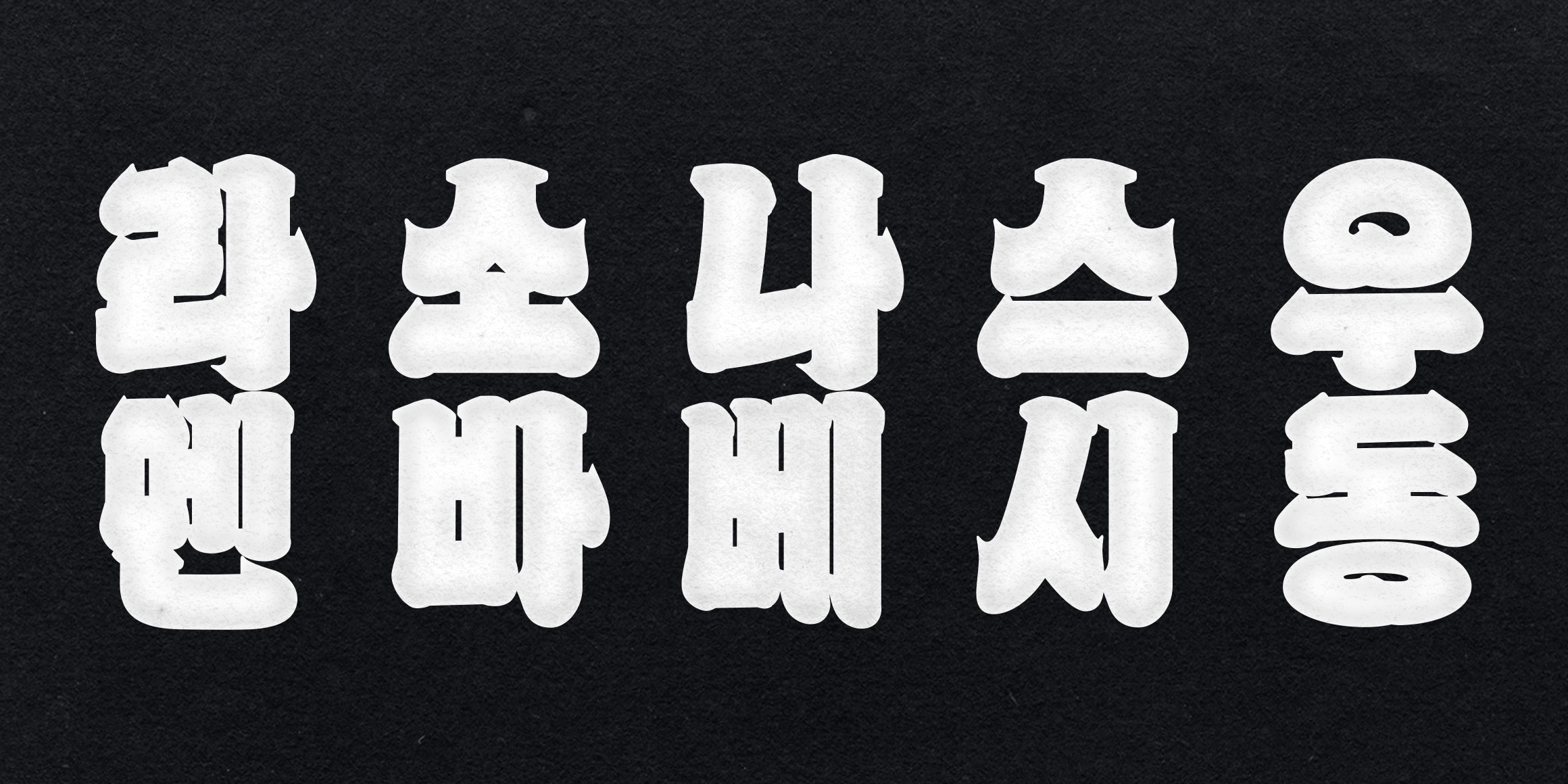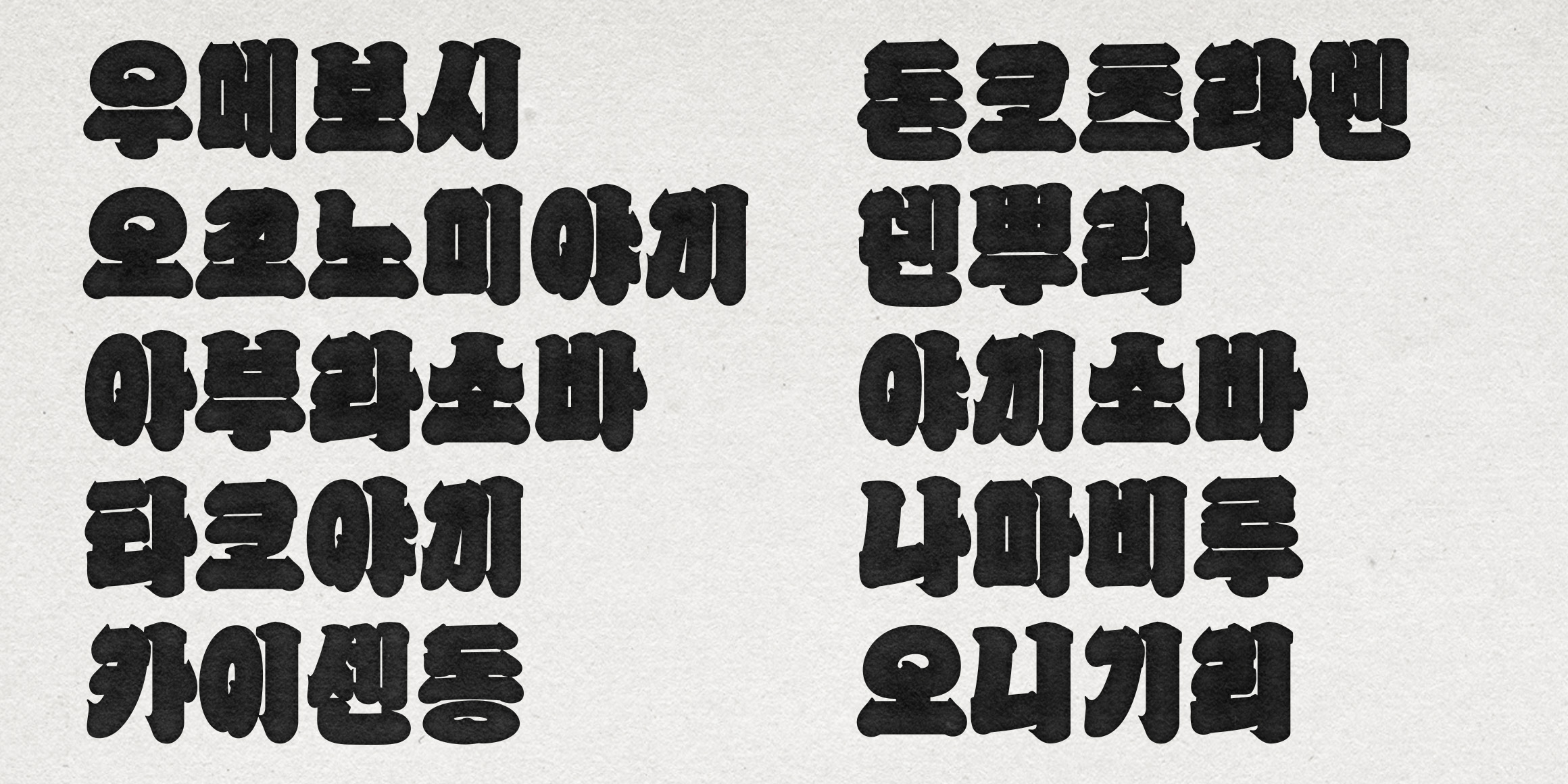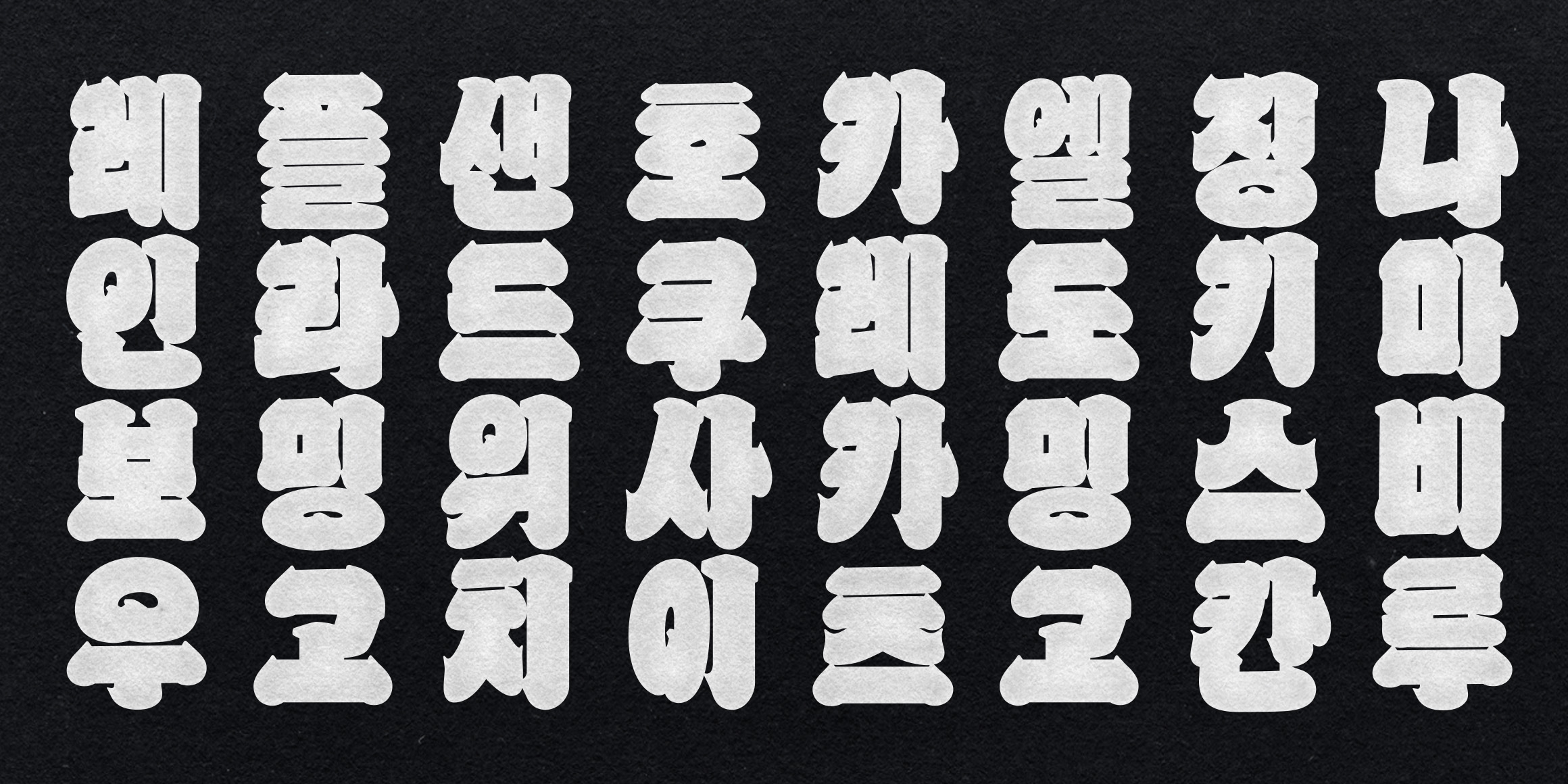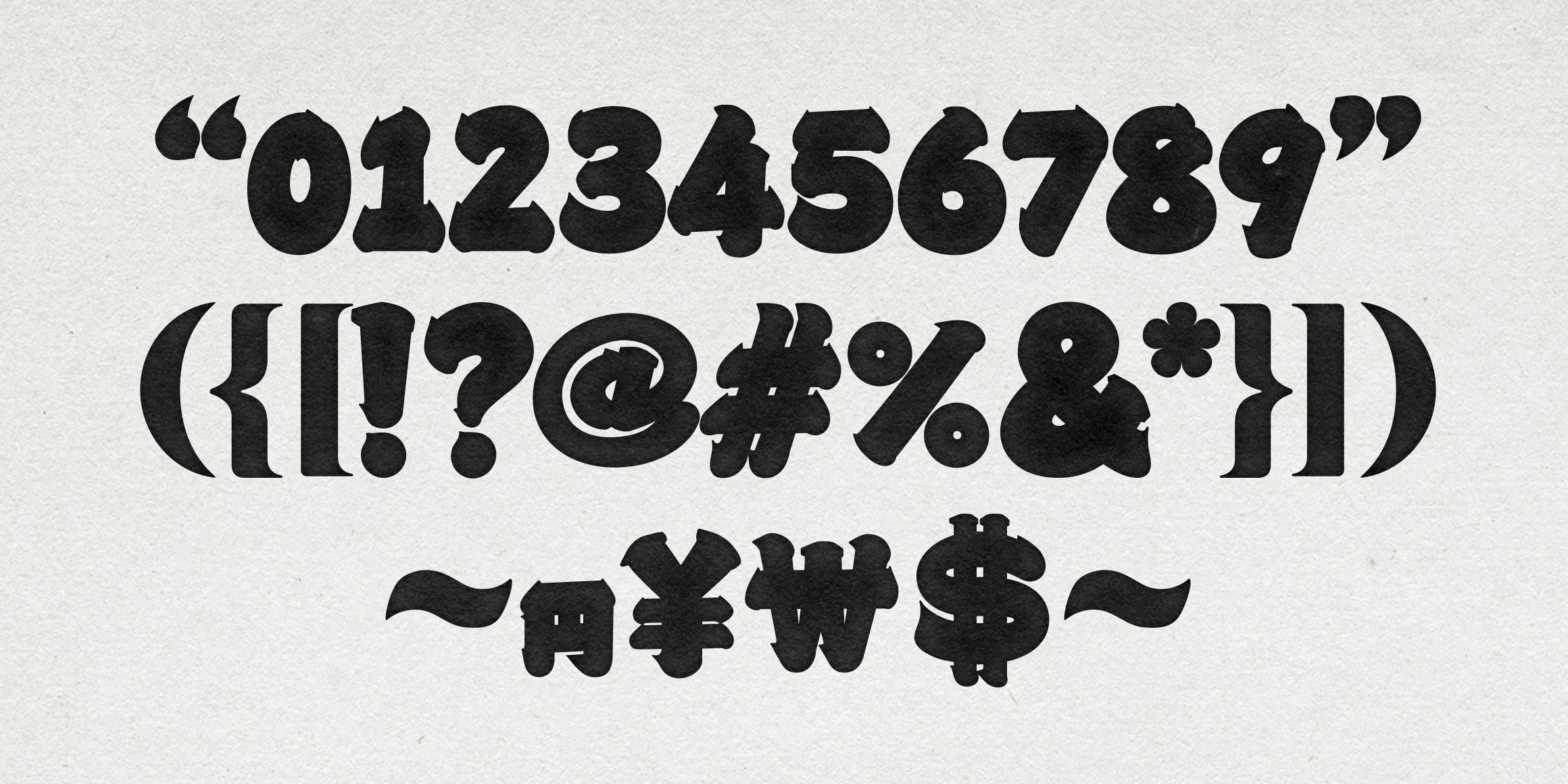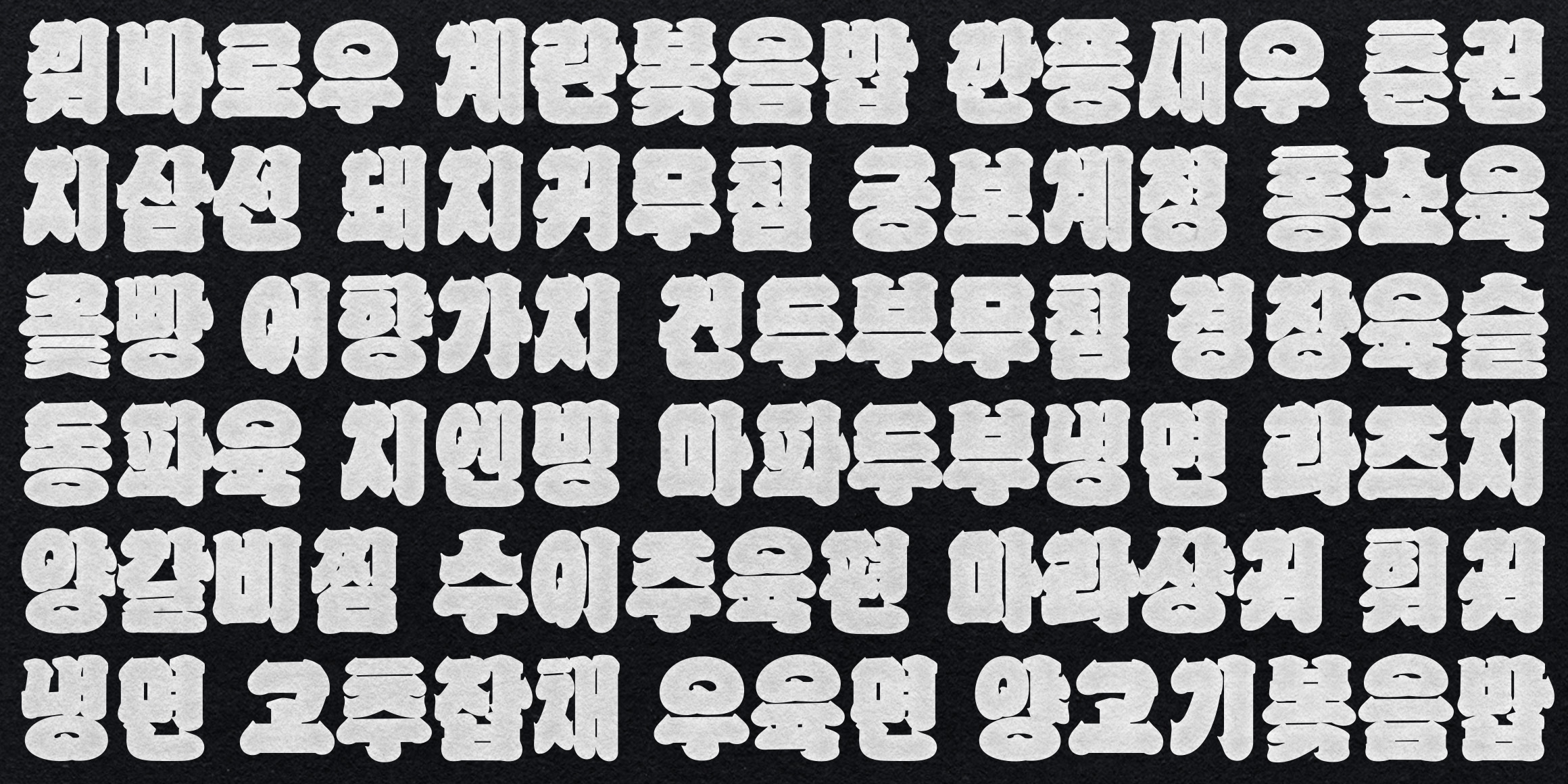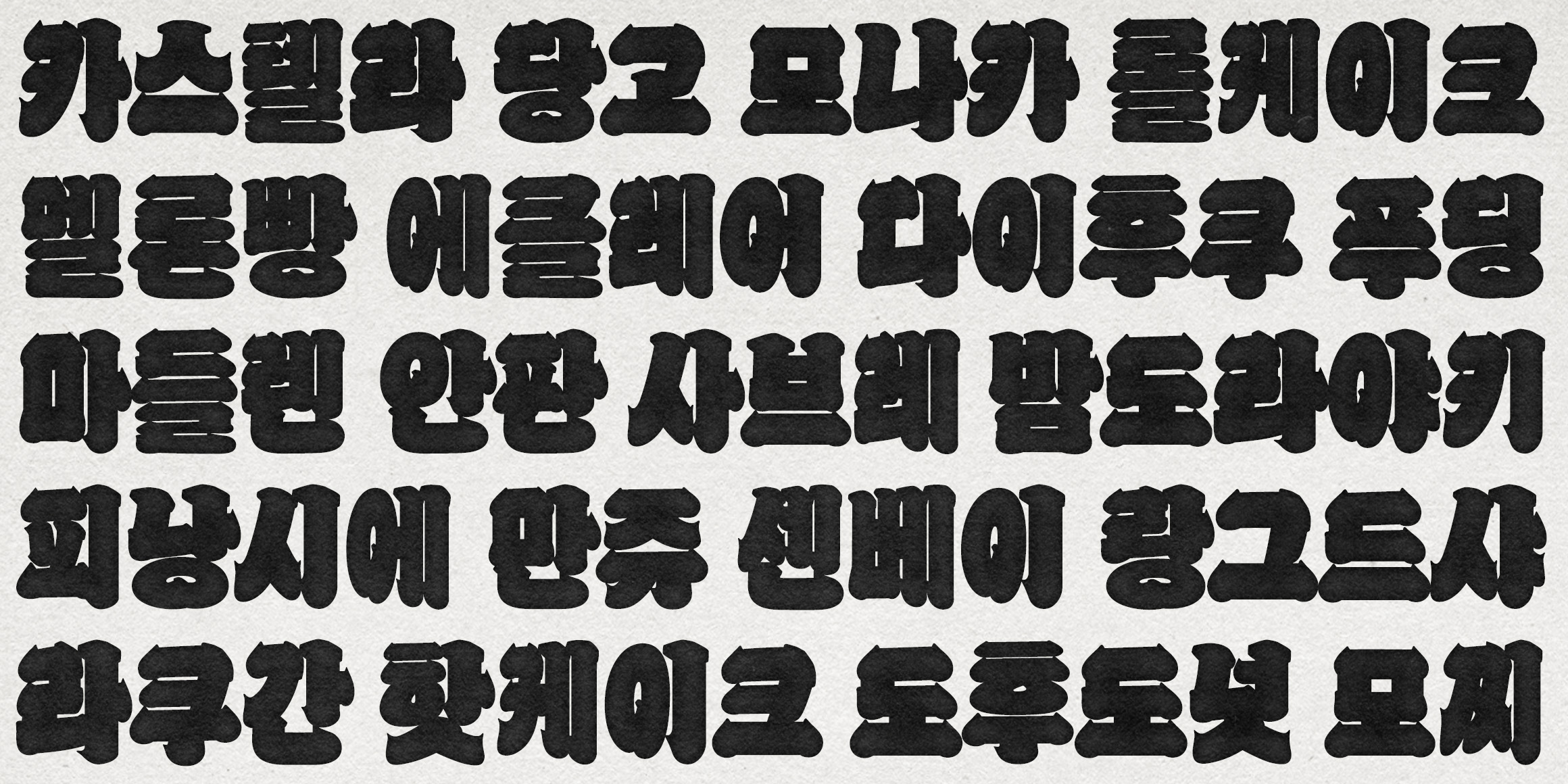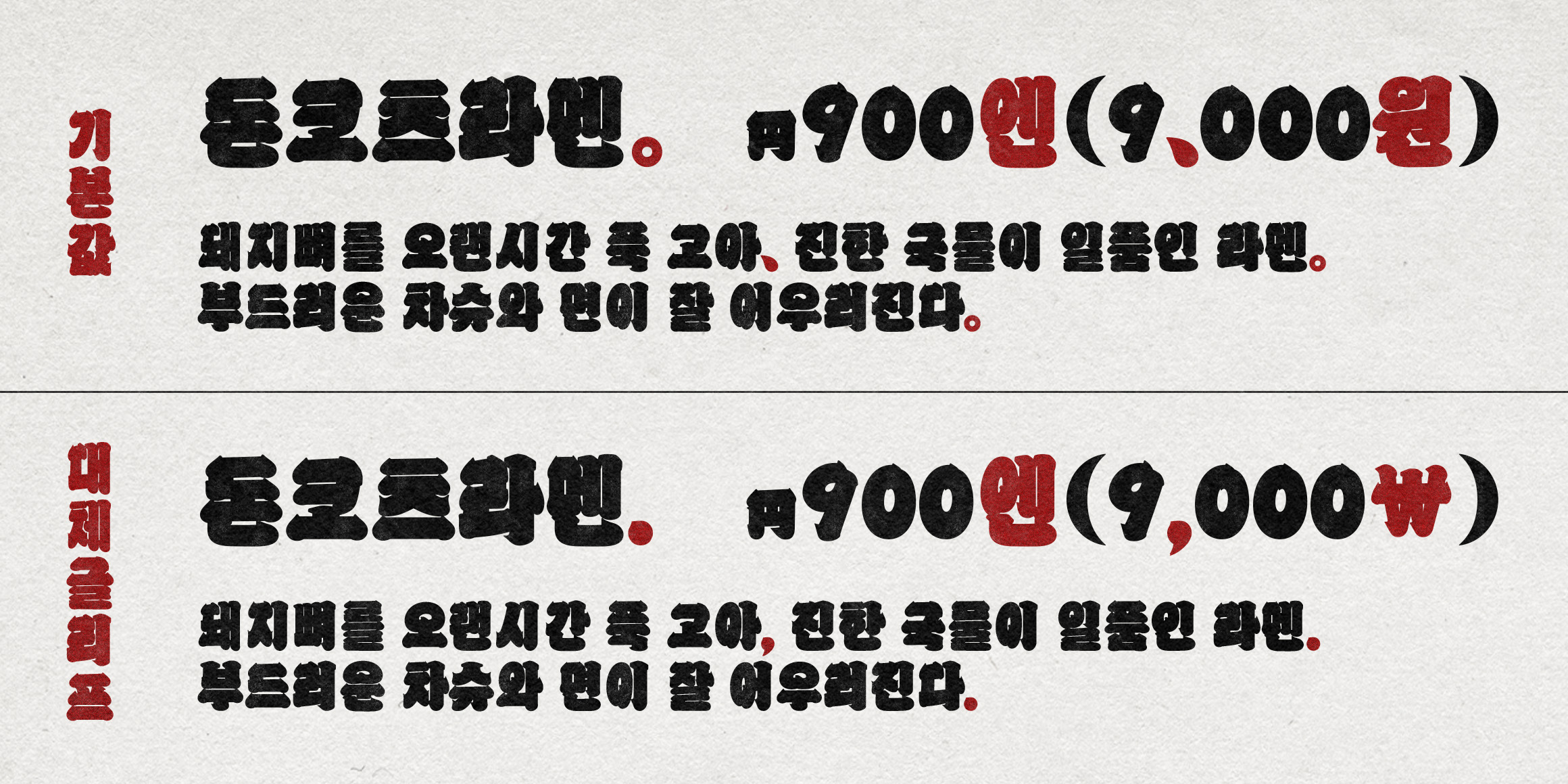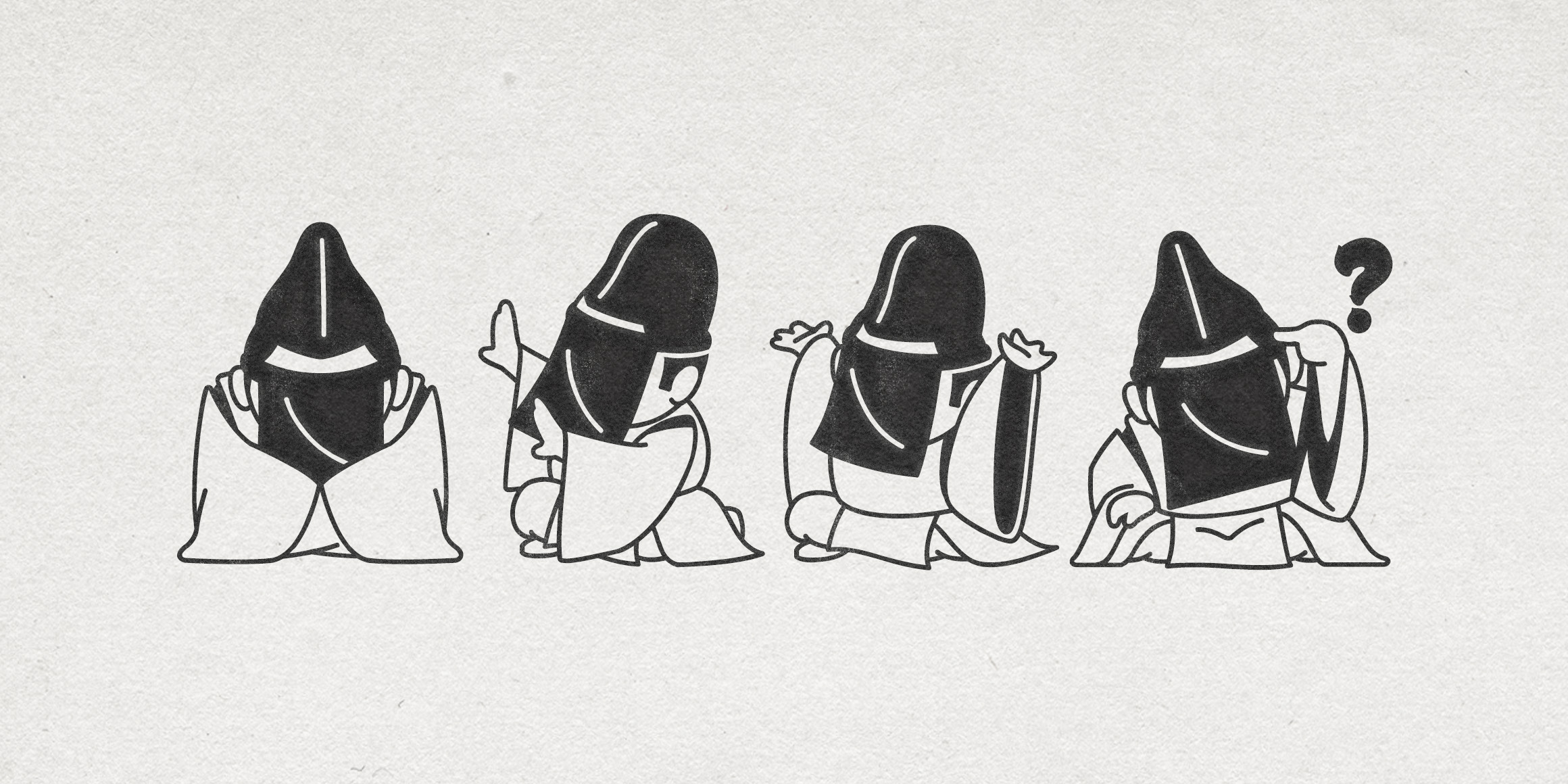
K110 쿠로코체 카고
분류 디스플레이,손글씨
종수 3종
제목용출판고전적
[K110 쿠로코체 카고]는 일본의 역사 깊은 글자체인 에도모지(江戸文字), 그중에서도 카고모지(籠文字) 스타일에서 영감을 받은 한글 서체입니다.
기존 한글 서체가 2,780자로 구성된 데 비해, 이 서체는 일본어로 발음 가능한 글자들과, 범용성을 위해 추가된 글자들을 포함하여 1,950자로 구성되어 있습니다.
없는 글자가 입력될 경우 쿠로코가 등장해 기존에 없던 독특한 타이핑 경험을 선사합니다.